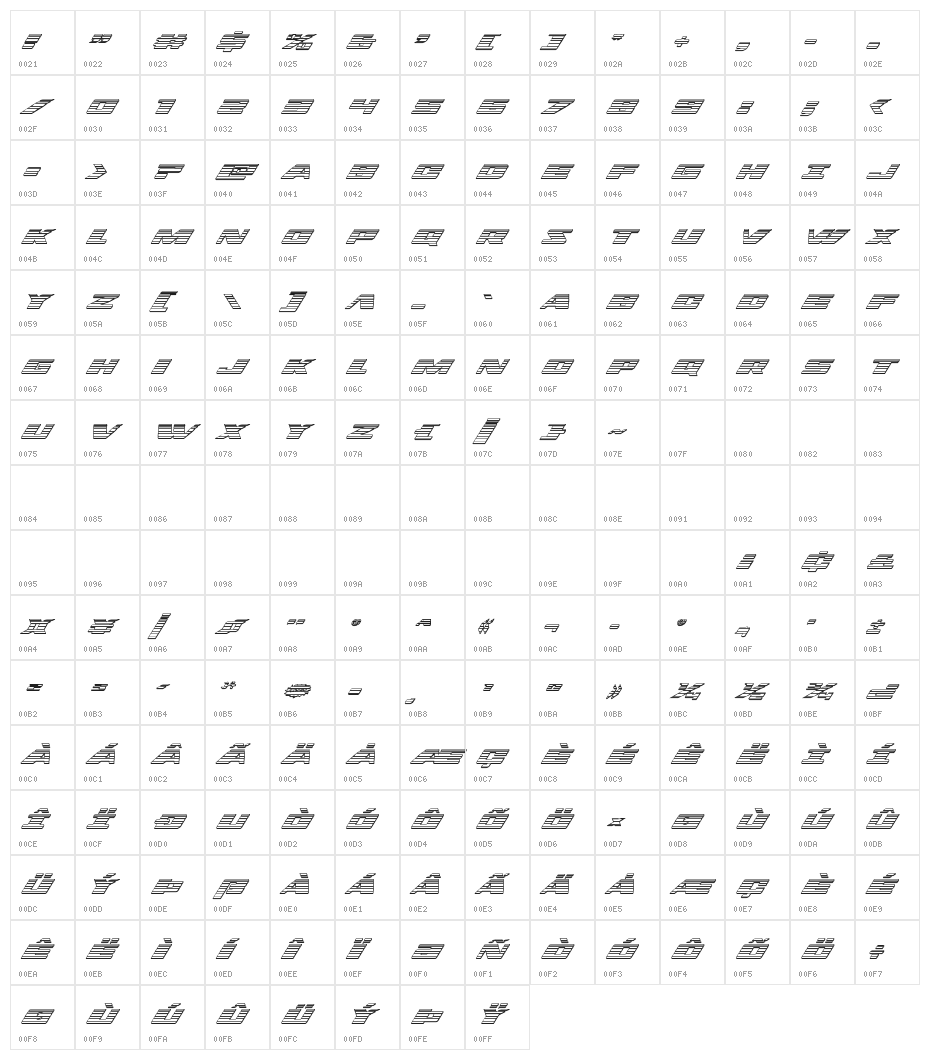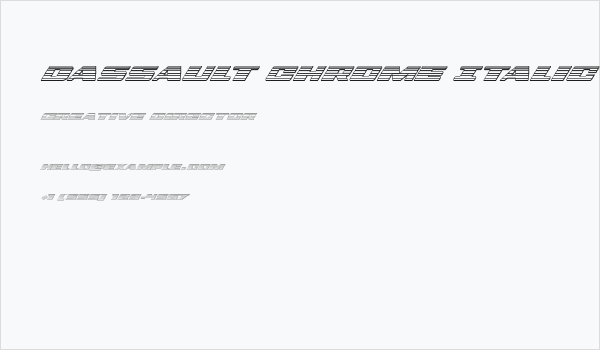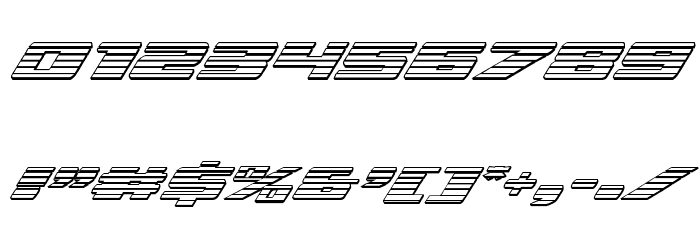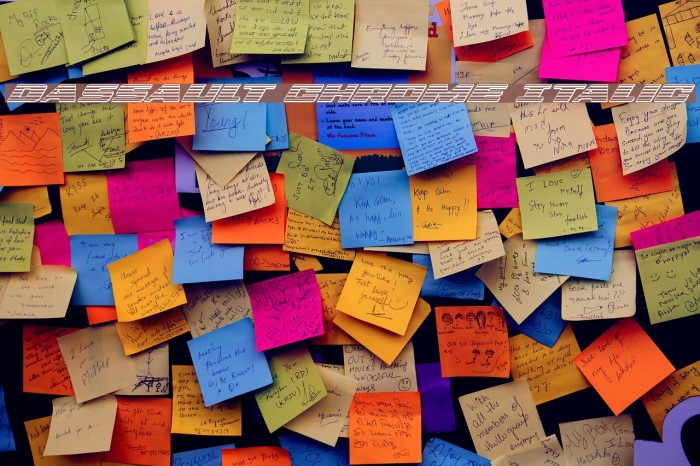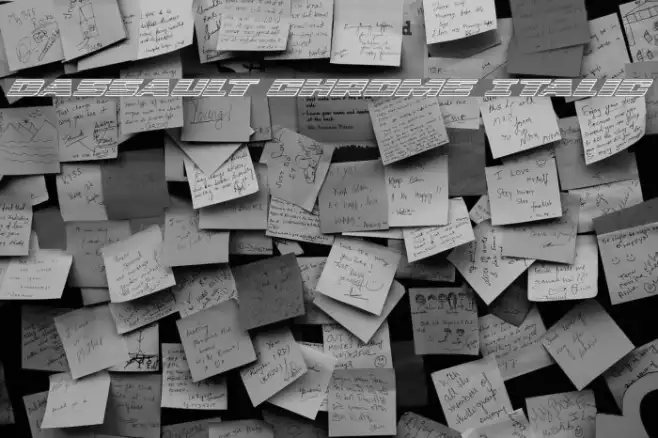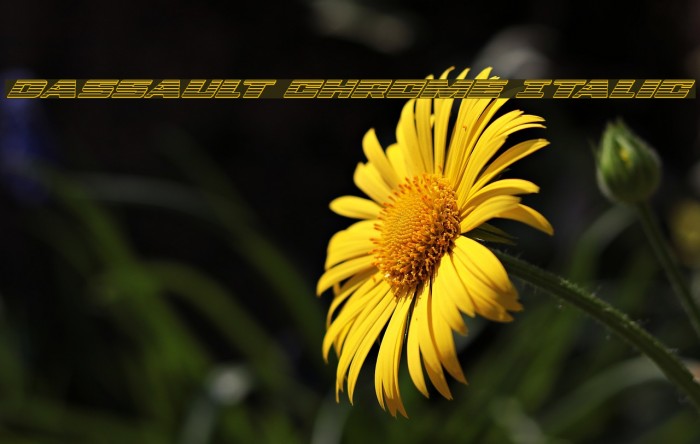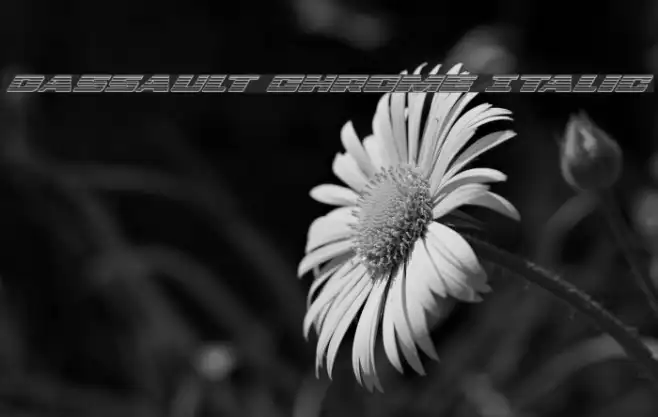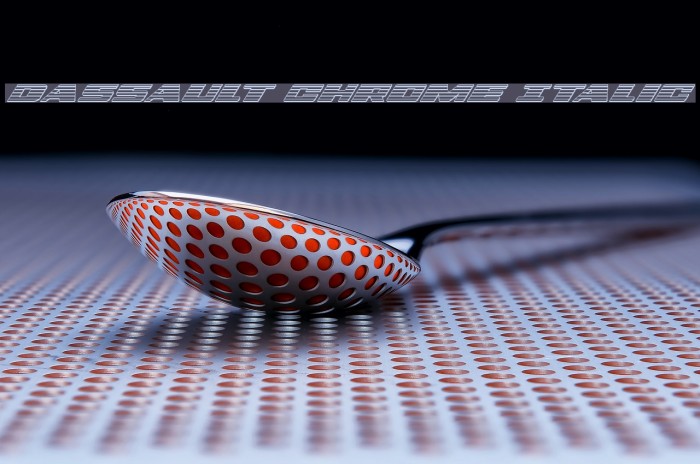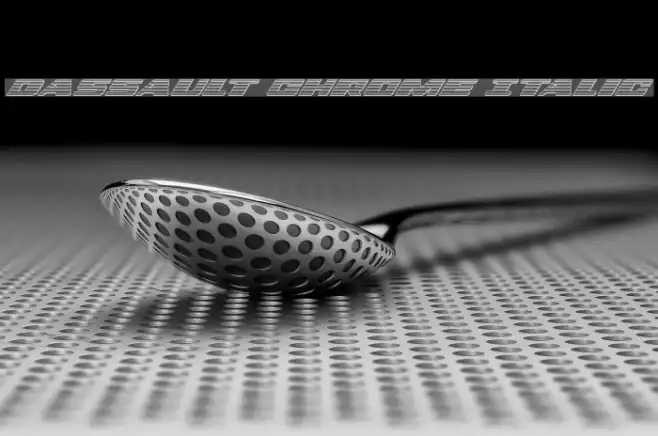
Dassault Chrome Italic Font
| Caso de uso | Logos, Headlines, Posters |
| Proyectos propuestos | Ideal for sci-fi themed designs, automotive branding, tech-related logos, and modern advertising campaigns. |